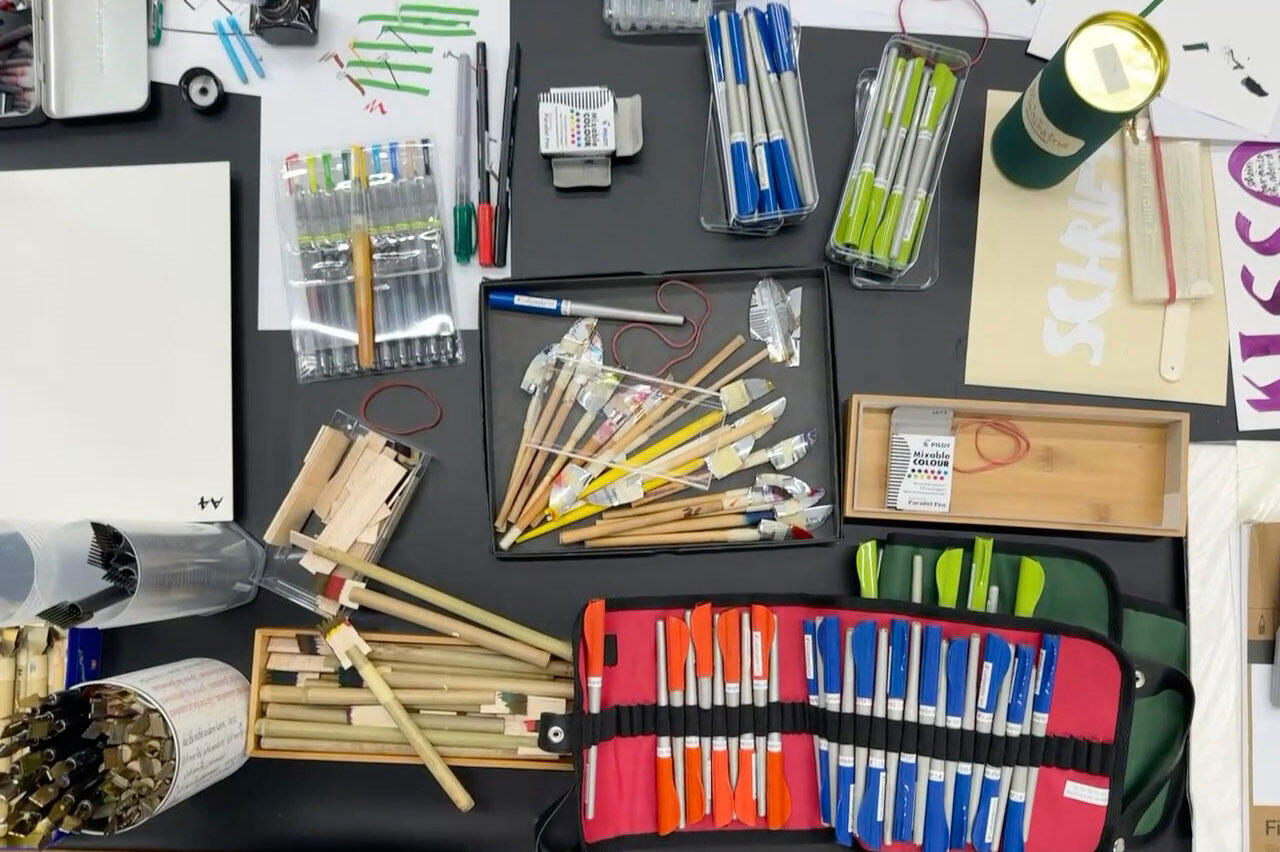
Kalligrafieseminar mit Andreas Frohloff (Wernigerode)Seminar Teil 1: Grundlagen der Kalligrafie
Seminar Teil 2: Freie Anwendungen der Kalligrafie
Ein unvergessliches Wochenende mit Andreas Frohloff und seiner professionellen Anleitung und Einführung in das Schreiben einer Breitfeder-Kursiv nach den Schreibmusterblättern von Axel Bertram mit einem kleinen Einblick in die Besonderheit der »Wandlitzer Schule«.
Die typischen Schreibspuren unserer Schrift wurden und werden immer noch durch die Breitfeder erzeugt. Dieses formbildende Werkzeug hat entscheidenden Einfluss auf die Gestalt der Buchstaben.